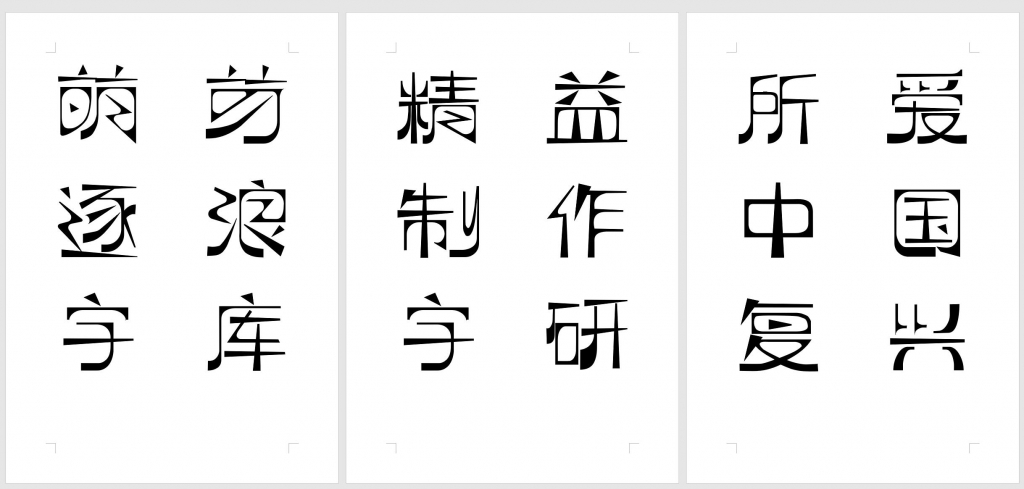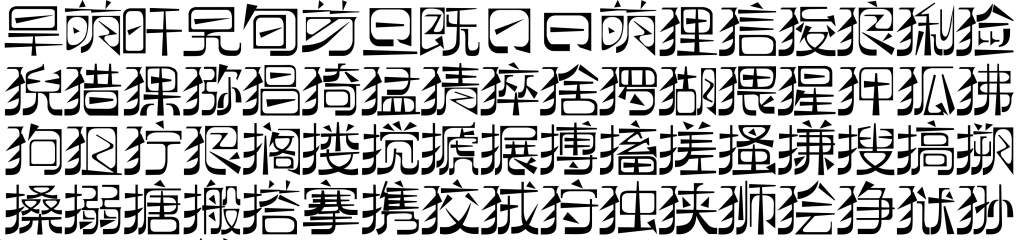
一款参照近代中国共产党《萌芽》月刊的艺术字体。 源自五四运动文化,力求体现近代文艺风。
字体线条呈现外方内圆格局,有尖锐的外角、三角部件,而内部空间则呈现圆形切割效果。 这体现了五四、清末民初,在工业革命思维冲击下,一代文化人对于中国汉字的探索。 又似布尔什维克人的工人、工业文化在汉字下的体现。
尖锐、锐角三角形的部件,从中体现了上进、革命、进击。
结字扁形,即左右宽度大于上下高度。
- 1.外角采用尖角,内角采用弧角
- 2.是一个抽象的孤形字。
- 3.试图创造上个世纪30年代“左联”的手写字体风格,该风格是用于出版物出版,简朴又不失艺术性。
- 4.多弧形、多三角形。
- 5.整体偏矮宽方正型,非常规字体,异型字居多
- 6.笔画粗细对比明显,角的笔画相对横竖线要粗
- 7.竖线笔画下端粗上端细,横线笔画左边粗右边细
- 8.外角整体偏方形,内角整体偏圆形的创意字体
- 9.整体风格硬朗纤细
“逐浪萌芽字”是一款书写很新颖的字体,字体大方,适合各种设计作品使用!欢迎下载!